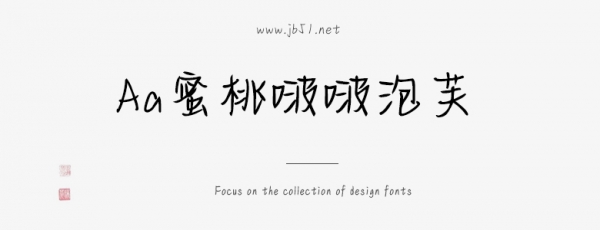
Aa蜜桃啵啵泡芙是一款不錯(cuò)的藝術(shù)字體,由Aa字庫出品,字體筆觸略細(xì),書寫流暢,擁有字符數(shù)8215和字形數(shù)8183,具有很好的視覺感,適合應(yīng)用于藝術(shù)設(shè)計(jì)、平面宣傳設(shè)計(jì)、網(wǎng)頁設(shè)計(jì),書法字帖等領(lǐng)域,需要的朋友可以前來本站下載。